近日,大连城市LOGO大赛评选结果出炉,有网友指出,获奖作品大连城市LOGO涉嫌抄袭迪士尼的LOGO,英文字体部分都是直接照搬。与此同时,书法家“叶根友”在微博声称,大连城市LOGO里的中文“大连”二字,也都是自己的字体,使用没有经过授权。大连市文化和旅游局回应东方网·纵相新闻记者称:“目前正在调查走程序中。”
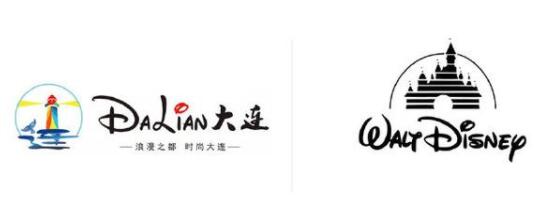
据了解,大连市文化和旅游局自6月26日开展了“大连有好礼”首届大连文化创意和旅游纪念品大赛,在不到三个月的时间内,共收到了参赛作品近千件。经过激烈且严格的评审,最终选出礼品统一外包装形象及logo设计类、创意设计类、实物类三大类别共34个获奖作品。
12月12日,大连发布公布了《首届大连文化创意和旅游纪念品大赛》最终的获奖作品结果,其中作品名称为“大连城市LOGO”的LOGO设计获得了该板块的头奖。根据官方发布信息,该设计以汉字“大连”进行演变,由“铁山灯塔”“月光海”“嬉戏海豚”“大连”中英文标准字组合而成,“将城市名称和视觉形式合二为一,简单几笔的设计,将大连的城市特色体现得淋漓尽致。”
但是,相信很多人在看到这个获奖作品的时候,都会觉得似曾相识,总觉得在哪里见过。
对了,就是迪士尼的LOGO!
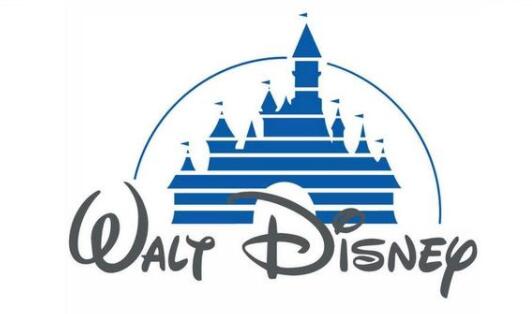
仔细比对就会发现,“DaLian”这几个字母,与迪士尼的英文高度相似,其中字母D、A、N基本完全一样,字母i图形一致,只不过,上面的点迪士尼是黑色,该作品将这个点改成了红色。
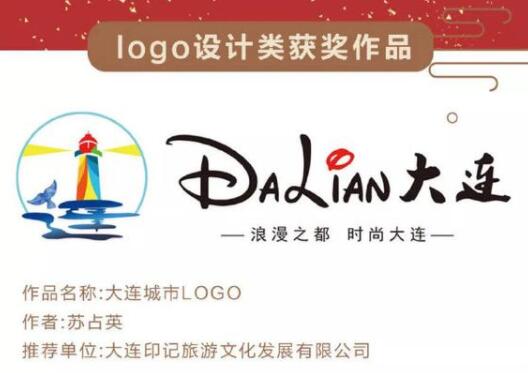
这样仔细比对下来,感觉只有L这个字母是半原创,但这又继续被网友“打脸”。有“眼尖”的网友指出,虽然迪士尼的LOGO中没有L这个字母,但是再细看,这个L仿佛是“Walt”的那个t放大、翻转而来。
好了,这下DaLian6个字母“全军覆没”了,今天上午,书法家叶根友进一步爆料,获奖作品中“大连”这2个中文字体,也不是原创,而是取自自己的叶良友字体,且没有经过授权。
获奖作品信息显示,推荐单位为大连印记旅游文化发展有限公司,作者为“苏占英”,记者在天眼查中获悉,苏占英为该公司法定代表人,其名下一共有3家公司。
今天下午4时,东方网·纵相新闻记者联系了大连市文化和旅游局,该局工作人员告诉记者,对于网上关于获奖作品涉嫌抄袭一事已经获悉,“目前正在调查走程序中。”
“大连发布”公众号关于评选结果的微信下面,官方置顶了一条回应,称文中公布的各种标识,只是获奖作品,并没有最终确定。获奖作品经举报侵犯他人知识产权的,一经查实,将取消参赛资格并追回奖励。违法国家法律规定等相关责任,由参赛者自行承担。